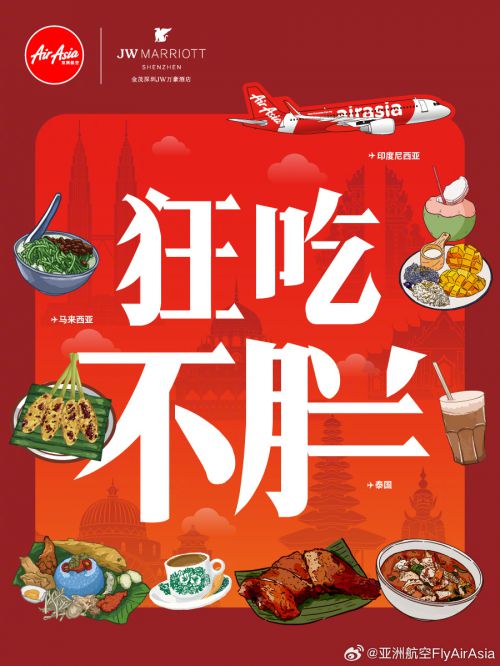
字由爱驾公路体-宋
字由爱驾公路体-宋是字由与爱驾传媒联合打造的创意宋体字库,以复古风格为基调,融合宋体的历史底蕴与公路文化的自由精神。作为“公路体”系列的全新成员,它打破黑体的科技冷感,以宋体特有的人文温度,重新诠释汽车与公路的时空故事。 字由爱驾公路体-宋字形方正稳健,重心居中平衡,中宫设计适中,既保留宋体端庄大气的经典骨架,又通过细节巧思增添现代活力。笔画处理上,直角转折利落分明,如公路干线般刚劲有力;部分笔画融入斜切设计,似车轮碾过路面的动态痕迹;方头笔触搭配断开式连接,粗细均匀中透着力量感,让每一笔都兼具历史的厚重与驰骋的轻盈。 这款字体以“传递悠久历史文化与人文精神”为核心,既适配汽车品牌视觉、公路主题海报等现代设计场景,也能在复古文化宣传、人文纪录片字幕中彰显独特韵味。字由爱驾公路体-宋,让宋体的典雅与公路的自由,在字里行间碰撞出穿越时空的魅力。